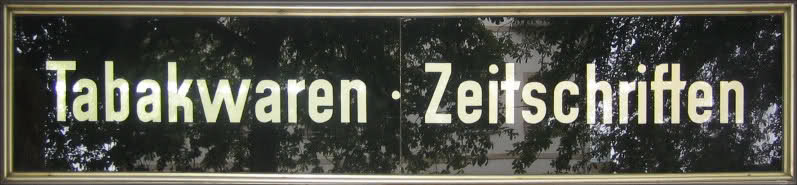
(Ältere) Ladenbeschilderung; eine DIN-Engschrift?
habe einmal ein Foto geschossen von einer etwas älteren Ladenbeschriftung. Und ich bin mir unsicher, ob es eine DIN Engschrift ist - ich glaube aber fast etwas ganz anderes.
Für die DIN ist das "k" meiner Meinung nach etwas zu verschnirkelt und ich bin nicht sicher ob es überhaupt Ligaturen gibt ("ft")...
Also: welche Schrift ist das? :)
(WTF spuckt mir natürlich nur die DIN aus und scheint nicht zu bemerken, dass das "k" halt anders aussieht...)
Handgeblasen und mundgemalt. Anleihen an die ganz alten Schriftmuster der Engschrift nach DIN 1451 (so ab 1906 aber vor der Gründung der Bundesrepublik) sind zu erahnen. Geometrisch konstruierte Schriften dieser Art findet man gelegentlich auch auf emailierten Straßen- und anderen Schildern.
Die Austria – die ehemalige Normschrift für Verkehrszeichen in Österreich – ist der gesuchten Schrift auch recht ähnlich, mit Ausnahme des Minuskel-k.